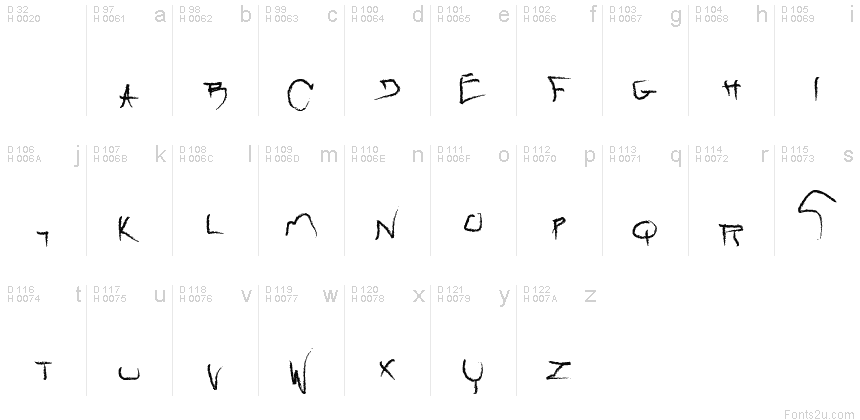
Raw autorstwa Nielsa Bonnevie to bezpłatny, ręcznie pisany font o nerwowej, poszarpanej linii, która bliższa jest gryzmołom niż dopracowanej kaligrafii. Litery wyglądają jak nakreślone suchym tuszem – z nierównymi pociągnięciami, surowymi łączeniami i niespokojnym, pionowym akcentem, który nadaje całości surowy, post-punkowy klimat rodem z dawnych fanzinów.
Świetnie sprawdza się na ulotkach muzycznych, plakatach, okładkach płyt, w tytułach filmów niezależnych czy surowym brandingu, gdzie font ma być wyrazisty, a nie grzeczny. Użyj go w krótkich nagłówkach, monogramach przypominających przybite pieczątki lub w wyrazistych inicjałach, szczególnie gdy chcesz, aby litery wyglądały jak szybko nakreślone ręcznie znaki.